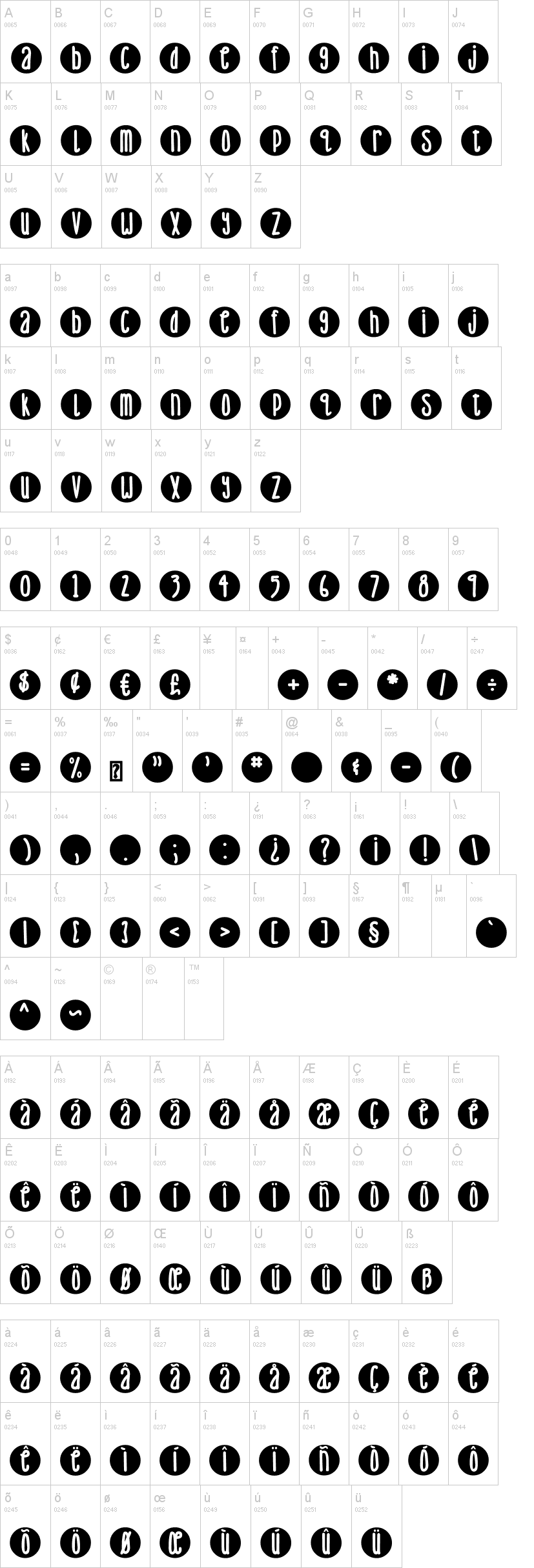
? DJB Lemon Head Dots 是由澳大利亚设计师Darcy Baldwin创作的一款手写字体,它具有清晰的外观,温柔优雅的设计,以及自然的曲线,它可以用于广泛的设计领域,从广告和标志到网页设计,报纸和杂志,甚至卡片和手写信件等。DJB Lemon Head Dots字体特别适合用于婚礼,节日和其他特殊场合,具有温暖的气氛和浪漫的感觉。内容介绍
DJB Lemon Head Dots是一款非常不错的手写艺术字体,具有很好的视觉感,适合于文化类的宣传设计、商业类品牌的广告和产品包装设计以及个性化文字排版等较多场景。